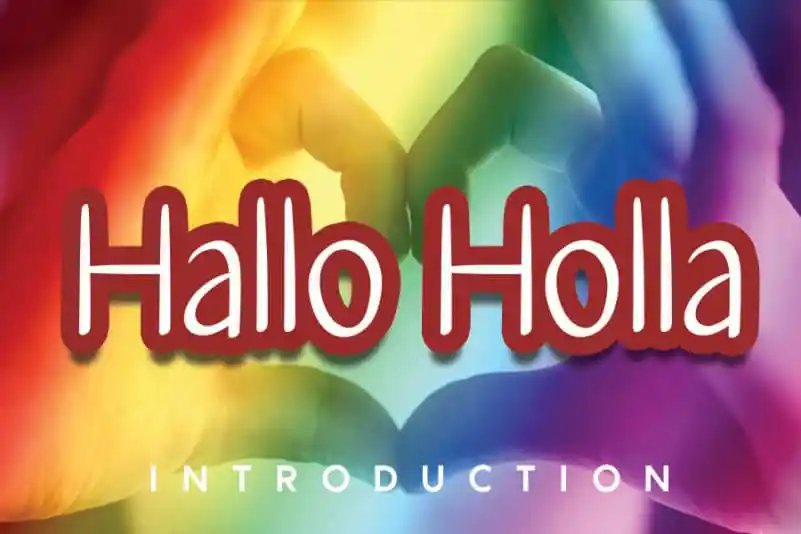
Hallo Holla Handwritten Font – Download Grátis
A ‘Hallo Holla Handwritten Font’ é uma elegante fonte cursiva com um ar encantador e amigável. Suas linhas naturais e personalizadas a tornam perfeitamente adaptável a um amplo leque de projetos gráficos, desde cartões de aniversário até materiais educacionais. A única limitação é sua criativa imaginação. Esta fonte serif é ideal para aqueles que buscam uma mistura suave e vibrante nas suas criações digitais. Sempre uma escolha ótima para quem procura um toque diferente, essa fonte é certamente capaz de fazer a diferença em qualquer design. Seja você designer ou criativo em geral, esta fonte certamente fará seu trabalho de acordo com as suas necessidades e conceitos pessoais. Descubra o poder da ‘Hallo Holla Handwritten Font’ e experimente seus próprios designs únicos!